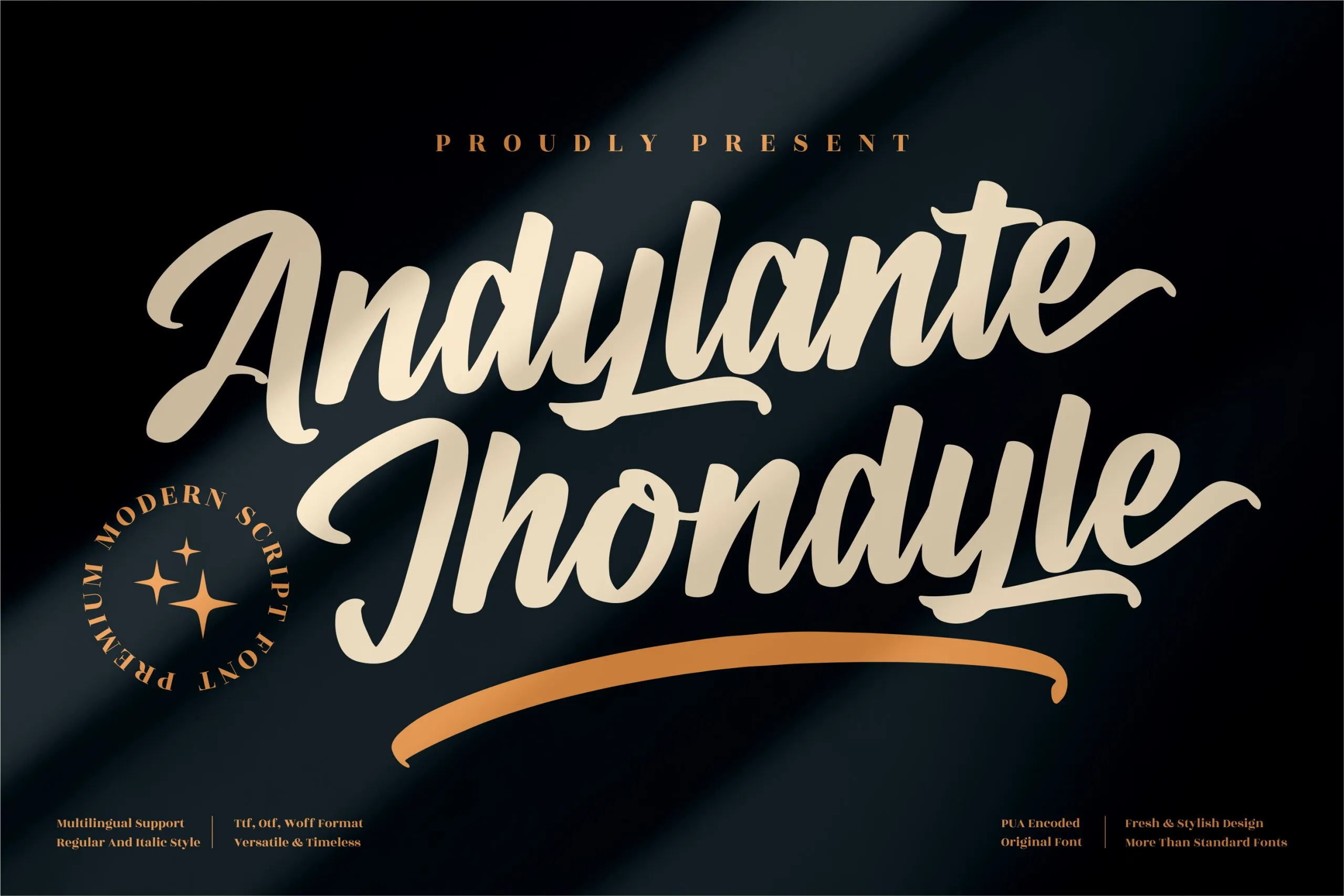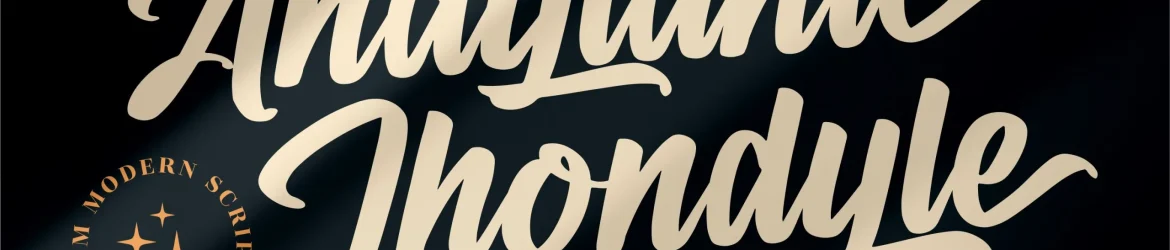
A “Andylante Jhondyle Font” é uma elegante assinatura que destaca-se por sua sofisticação e personalidade única. Ideal para projetos de alto nível, como criações de logotipos ou identidades visuais, estoques decorativos, embalagens de produtos, estojos de café com letrinhas, cartazes e flyers, sacolas de shopping, camisetas, capas de livros, cartões de visita, convites e cartões de agradecimento, etiquetas e até mesmo marcas em fotografias. Com um toque especial para designers que valorizam o luxo e a qualidade em cada projeto, esta font é uma escolha perfeita para qualquer tarefa onde uma assinatura autêntica se torna essencial. Ideal tanto para projetos de marca quanto para personalizações artísticas, a “Andylante Jhondyle Font” oferece o toque final que seu próximo projeto merece. Não importa qual tipo de trabalho você está realizando – seja um projecto pessoal ou profissional – a fonte “Andylante Jhondyle” será uma escolha inteligente e estratégica, garantindo sempre um resultado memorável e de alta qualidade.